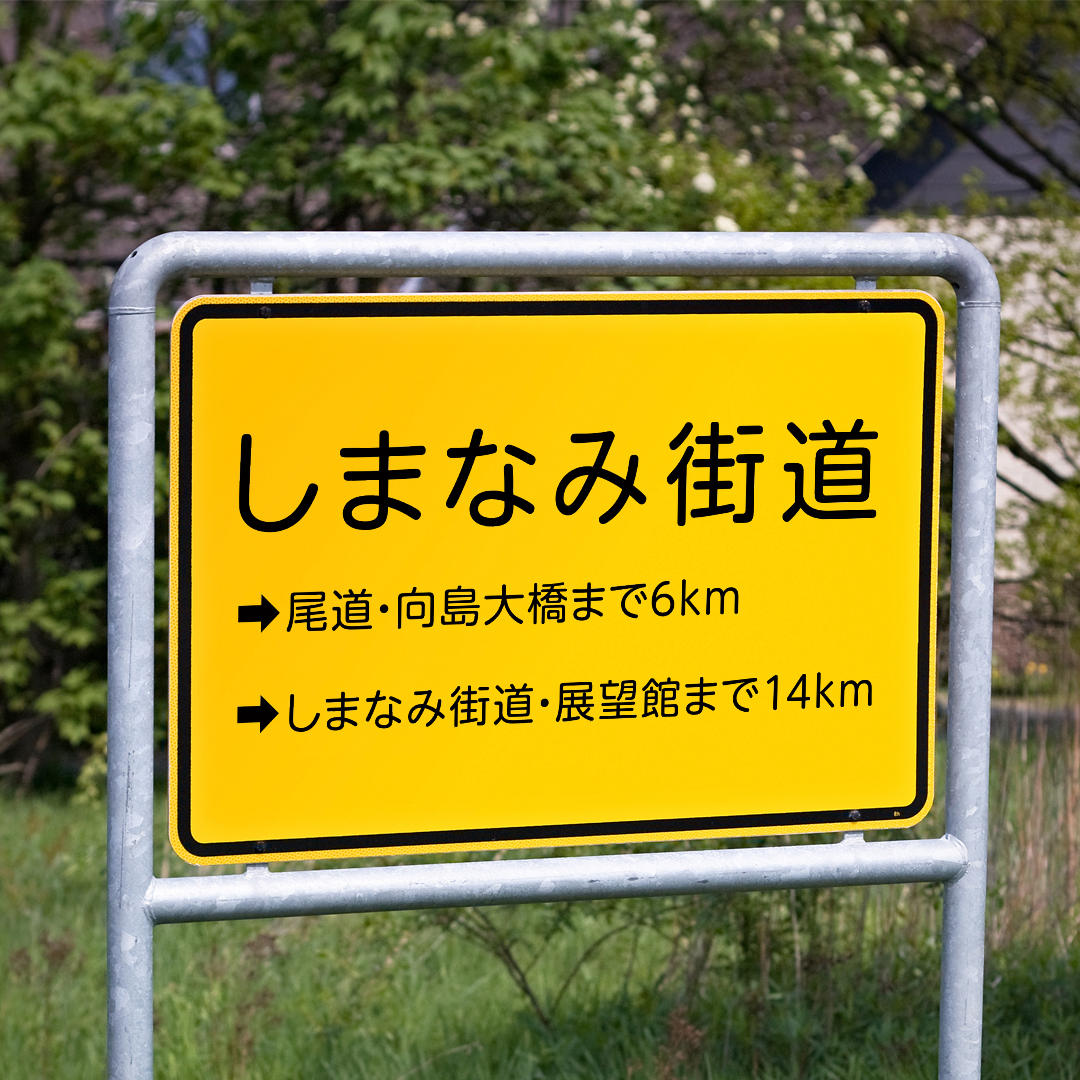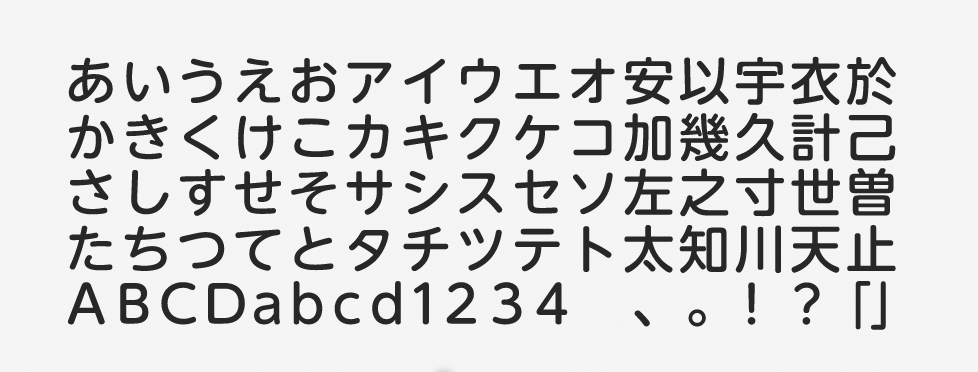
「UD新丸ゴ」について
UD新丸ゴは、丸ゴシック体の新丸ゴをベースとしつつ、ユニバーサルフォント化された書体です。本フォントをはじめとするモリサワUD(ユニバーサルデザイン)フォントは「文字のかたちの分かりやすさ」や「文章の読みやすさ」などを重視して開発されており、読者側が文字の読み間違えを起こしにくいことも特徴です。
「UD新丸ゴ」の特徴
UD新丸ゴは、ユニバーサルデザインに配慮しつつ親しみやすさや優しさを感じさせます。エッジに丸みがあって柔らかな雰囲気なので、絵本にも最適なフォントと言えるでしょう。
新丸ゴとの違いが顕著なのは、かな文字や英数字です。UD新丸ゴの字面は新丸ゴと比べてやや小ぶりで、文字の形もより手書きに近い自然なデザインが採用されました。英数字もシンプルなデザインで誤読を防げます。UD新ゴとの統一感があるため、あわせて使いやすい組み合わせです。
UD新丸ゴも、UD新ゴと同様に英数字のデザインが優れたフォントだと感じています。使いやすさが素晴らしく、モリサワの真骨頂とも言えるでしょう。個人的にも大好きなフォントで、よく使っています。ぜひ活用をオススメしたいフォントです。